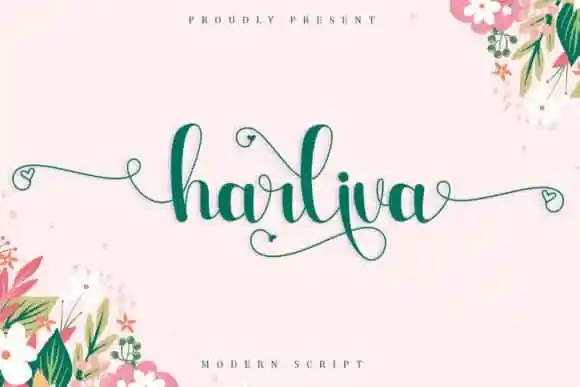
Harliva Calligraphy Font – Download Grátis
A Harliva Calligraphy Font é uma elegante e moderna tipografia à mão escrita que traz a naturalidade orgânica do texto humanoizado para sua obra de arte ou design digital. Esta fonte não apenas oferece uma ampla gama de letras maiúsculas e minúsculas, mas também inclui símbolos multilíngues, números, pontuação e ligaduras, tornando-a versátil e adaptável para uma variedade de projetos. Seja você um designer de branding único, trabalhando com fotos ou criação de efeitos fotográficos, criando cartões de convite, cartazes ou até mesmo desenhos em papel, a Harliva estará pronta para transformar suas idéias em obras de arte sofisticadas e bonitas. Esta fonte é uma opção perfeita para qualquer estilo, desde o jornalismo fotográfico até a moda e acessórios. Com sua simplicidade e beleza, a Harliva chama os designers para explorar seus infinitos recursos para criar designs que vão ao encontro do seu estilo e da sua marca.